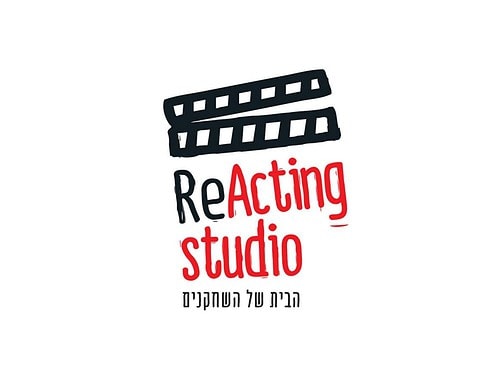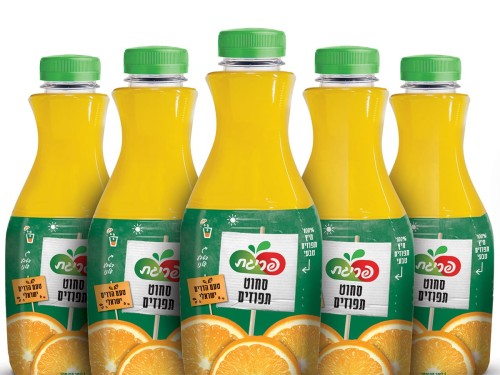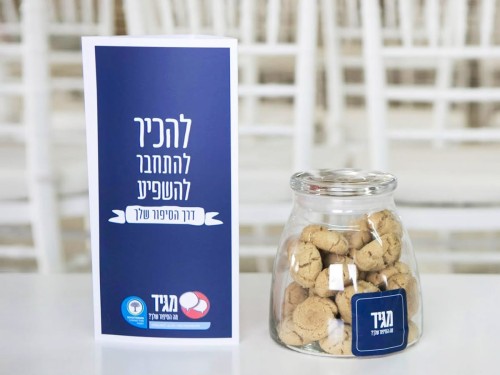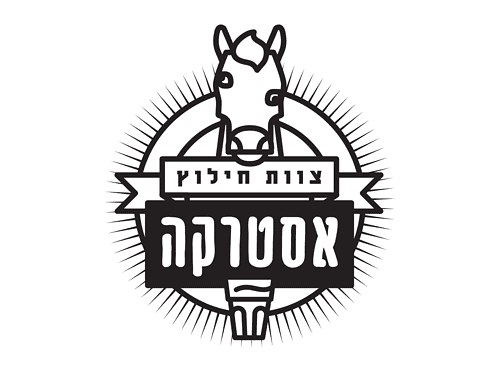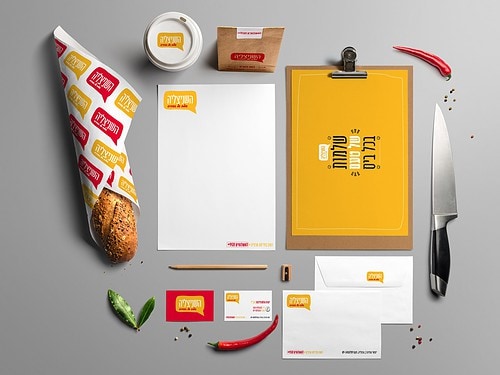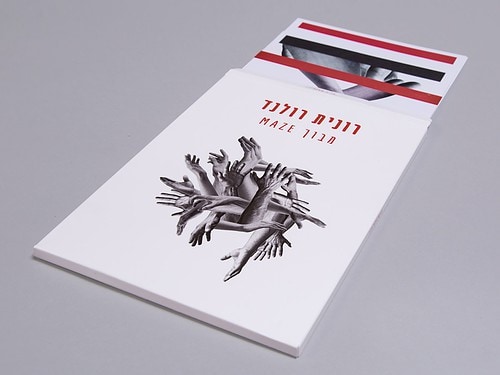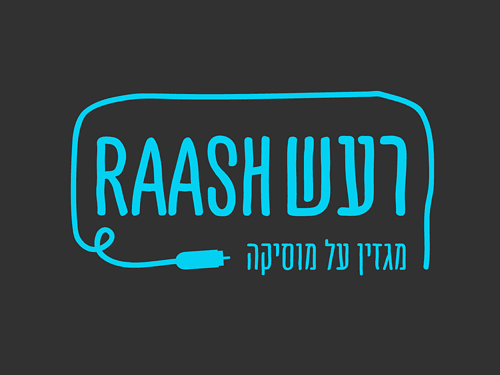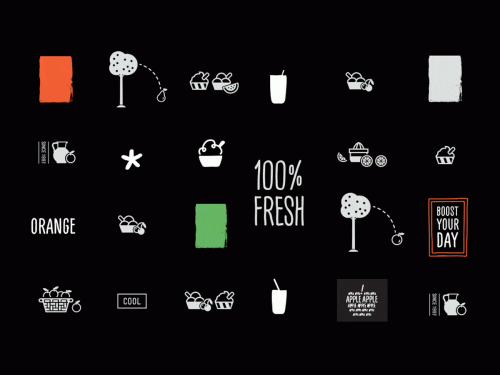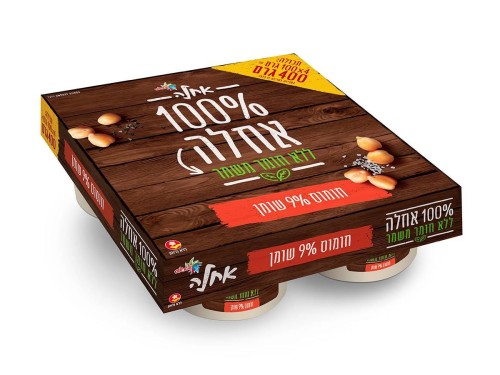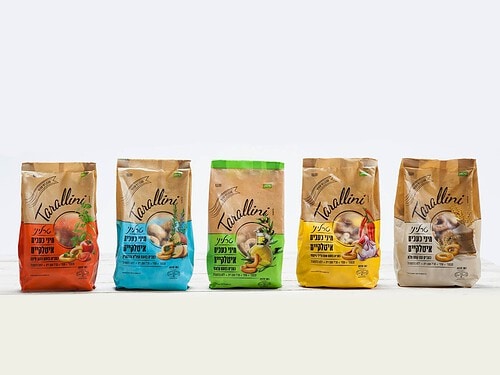
פונט כותרת ידני, כיפי ורענן בעל אותיות לטיניות וסט אייקונים מדליקים
If you're all about fun-fun-fun Mixtape is the perfect font for you
מיקסטייפ הוא פונט צעיר ושובב ויש לו אותיות חופשיות, כיפיות וטקטיליות. הוא כולל אותיות עבריות ולטיניות, סט אייקונים מדליקים והוא מגיע בשלושה משקלים סופר שווים.
על אודות פונט מיקסטייפ
פונט ידני, מדליק ורענן בעל אותיות לטיניות, סט אייקונים מדליקים והוא מגיע בשלושה משקלים סופר שווים. מיקסטייפ הוא פונט צעיר ושובב ויש לו אותיות כיפיות, חופשיות וטקטיליות.
הפונט הזה יקליל ויכייף לכם כל פרויקט